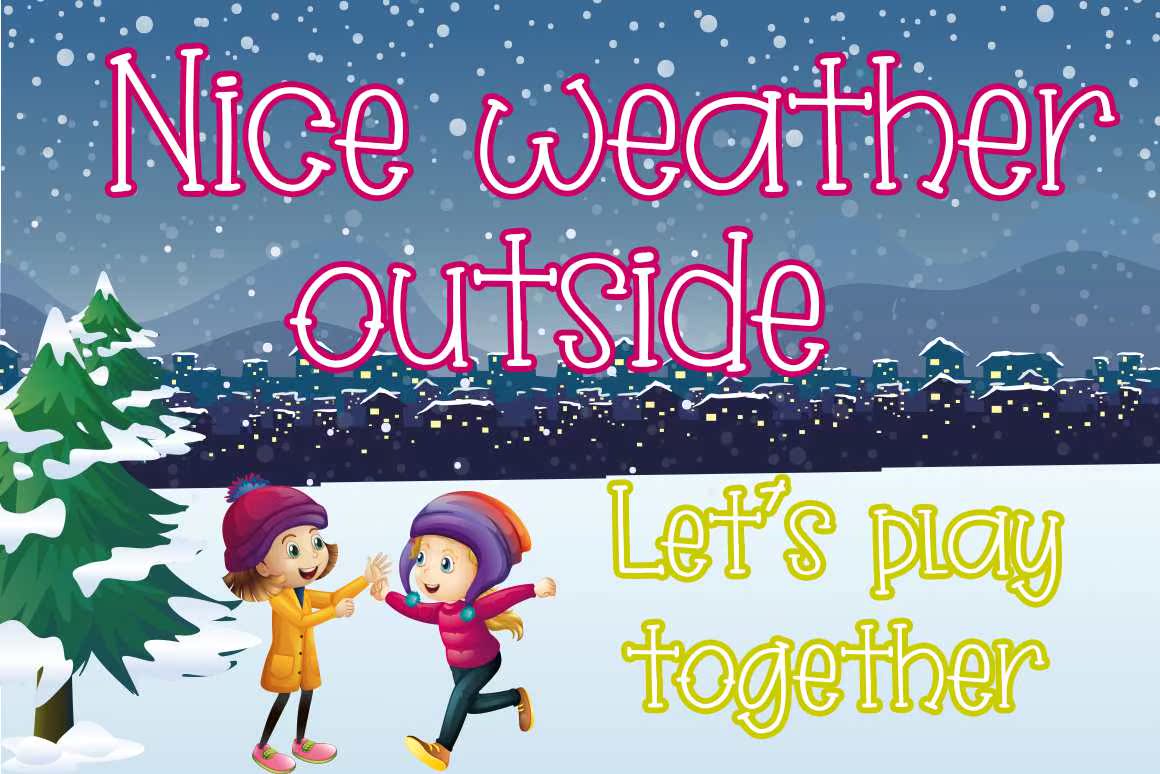
WinterBlissionIsquirky and CutEdisplayFont.It适用于您的Wintern and Christmas Projects Sands或您可以选择的任何其他项目。使用此字体构建您的创造力。WinterBlissionIsquirky and CutEdisplayFont.It适用于您的Wintern and Christmas Projects Sands或您可以选择的任何其他项目。使用此字体构建您的创造力。